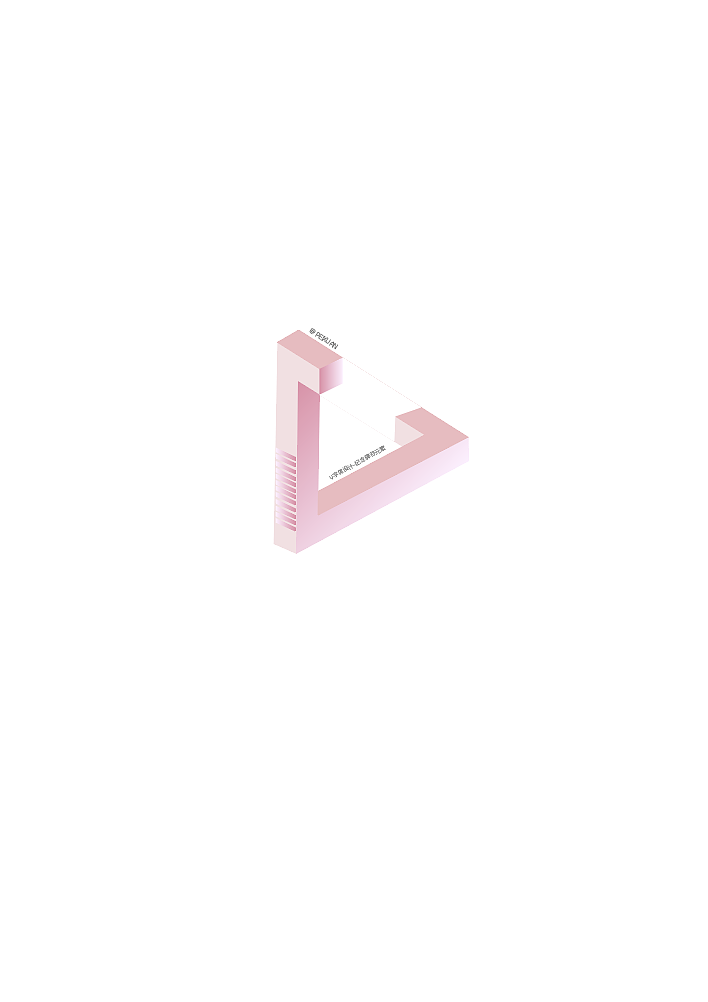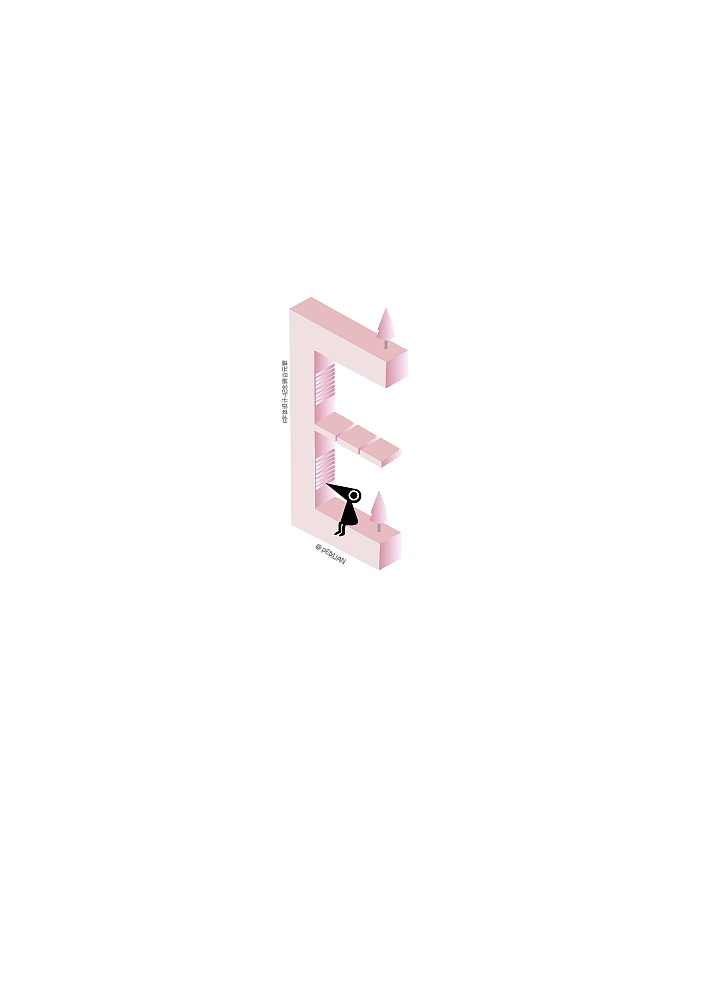
2.5D纪念碑谷元素的LOVE字体设计
2.5D纪念碑谷元素的LOVE字体设计(图ZOTgxNDE0NjQ=) - 字体/字形 - 站酷设计师PEIXUAN522原创素材 - 站酷ZCOOL
2.5D纪念碑谷元素的LOVE字体设计(图ZOTgxNDE0NzY=) - 字体/字形 - 站酷设计师PEIXUAN522原创素材 - 站酷ZCOOL
2.5D纪念碑谷元素的LOVE字体设计(图ZOTgxNDE0ODg=) - 字体/字形 - 站酷设计师PEIXUAN522原创素材 - 站酷ZCOOL
2.5D纪念碑谷元素的LOVE字体设计(图ZOTgxNDE1MTY=) - 字体/字形 - 站酷设计师PEIXUAN522原创素材 - 站酷ZCOOL
2.5D纪念碑谷元素的LOVE字体设计(图ZOTgxNDE1MzI=) - 字体/字形 - 站酷设计师PEIXUAN522原创素材 - 站酷ZCOOL